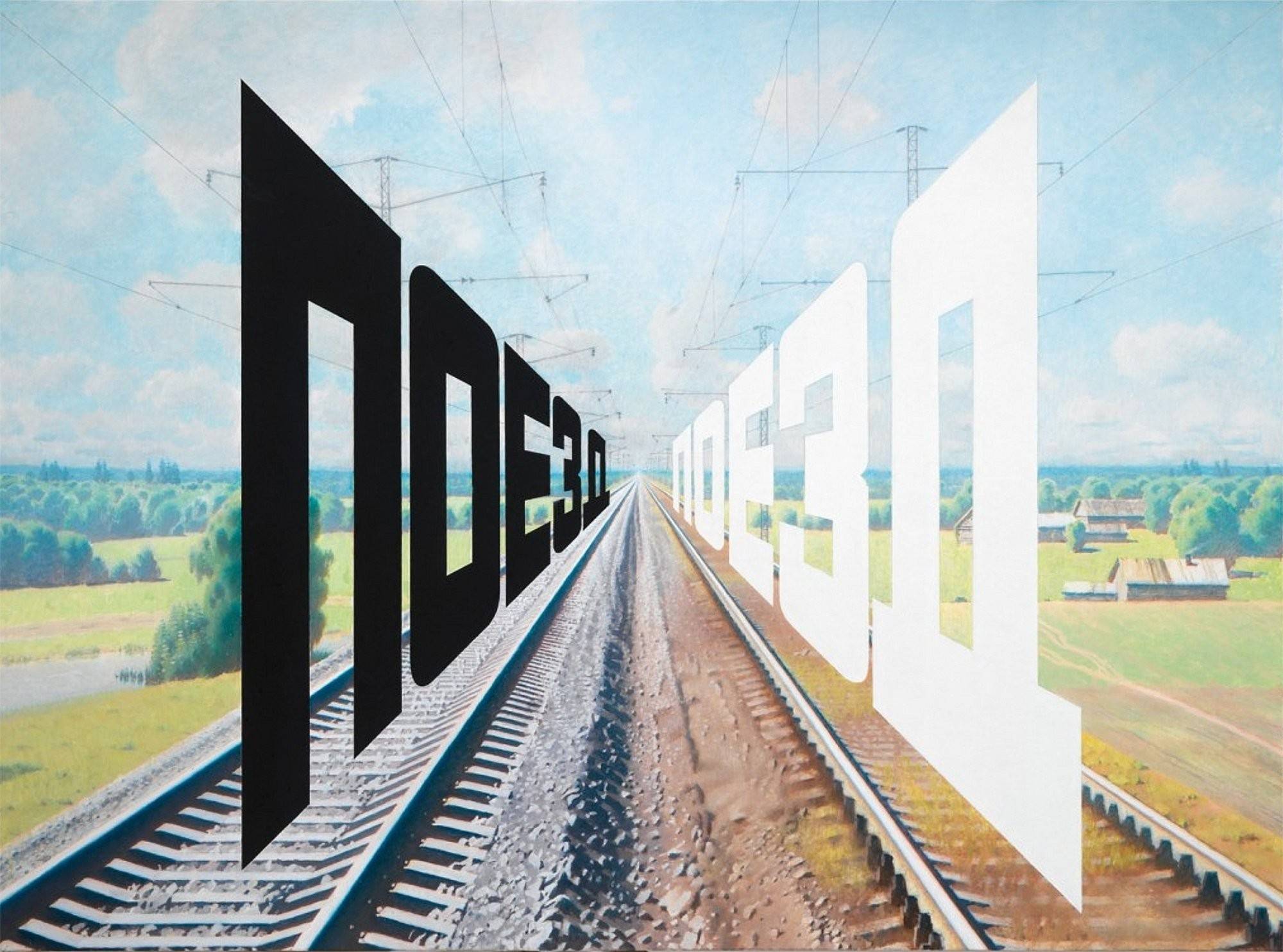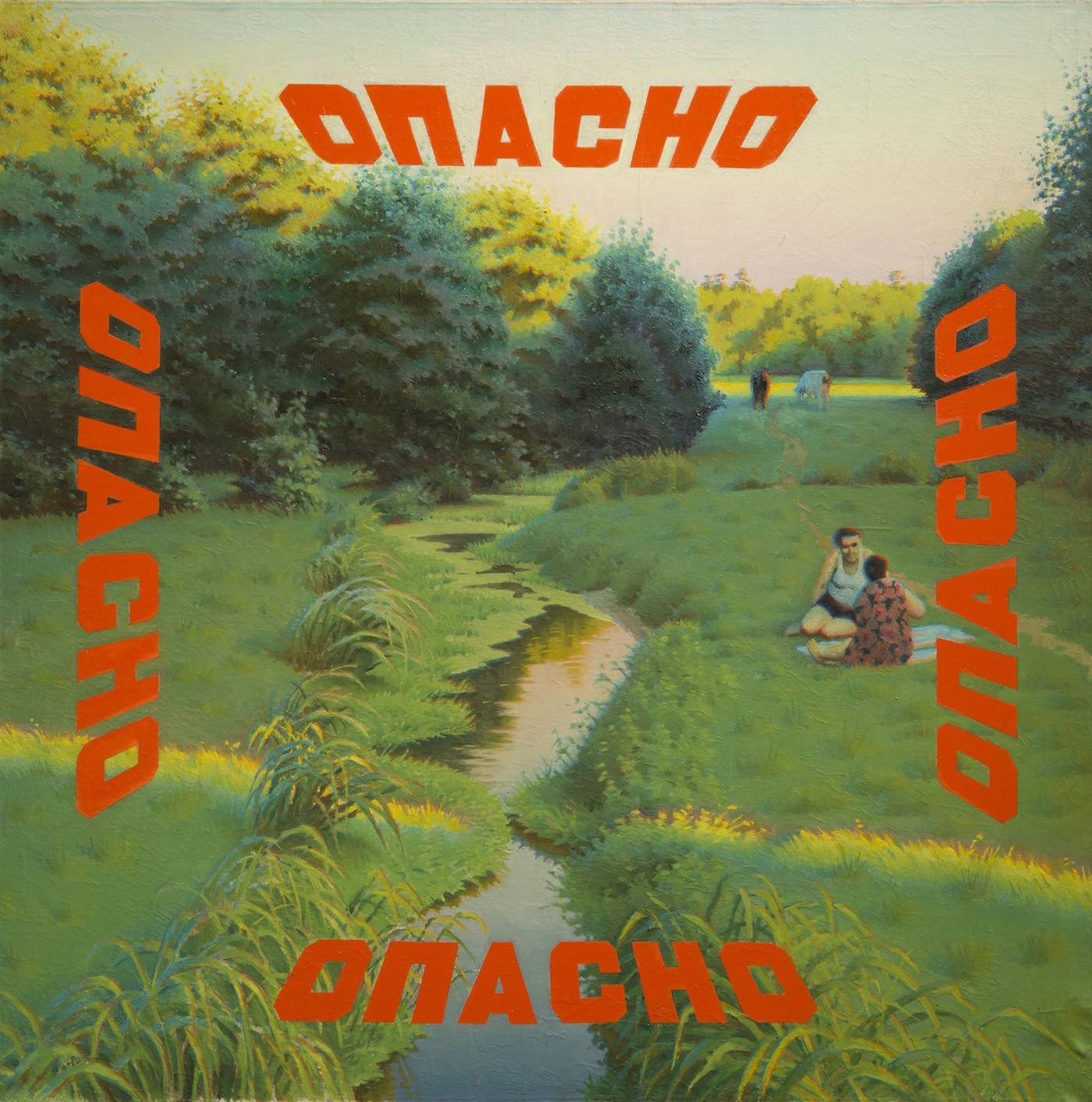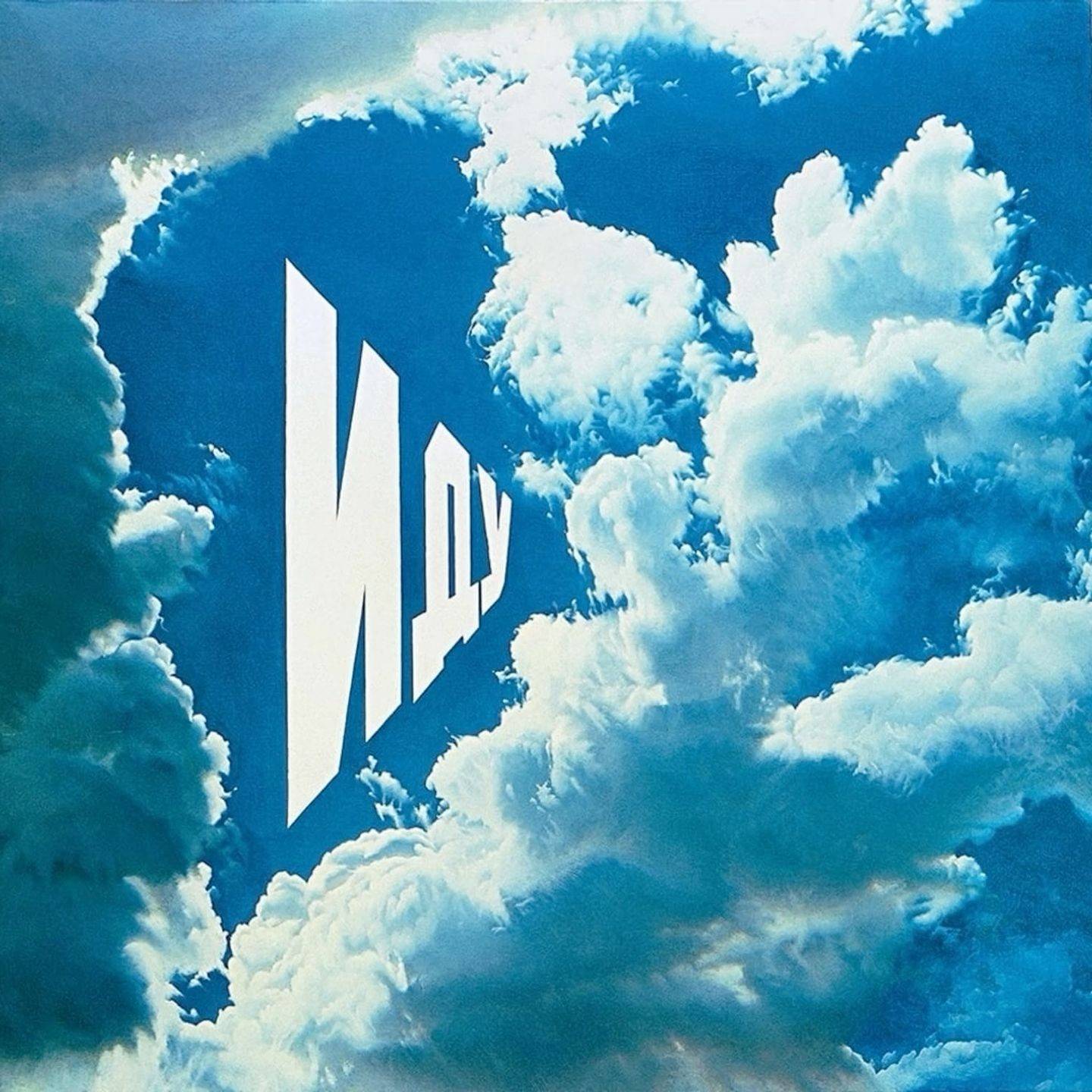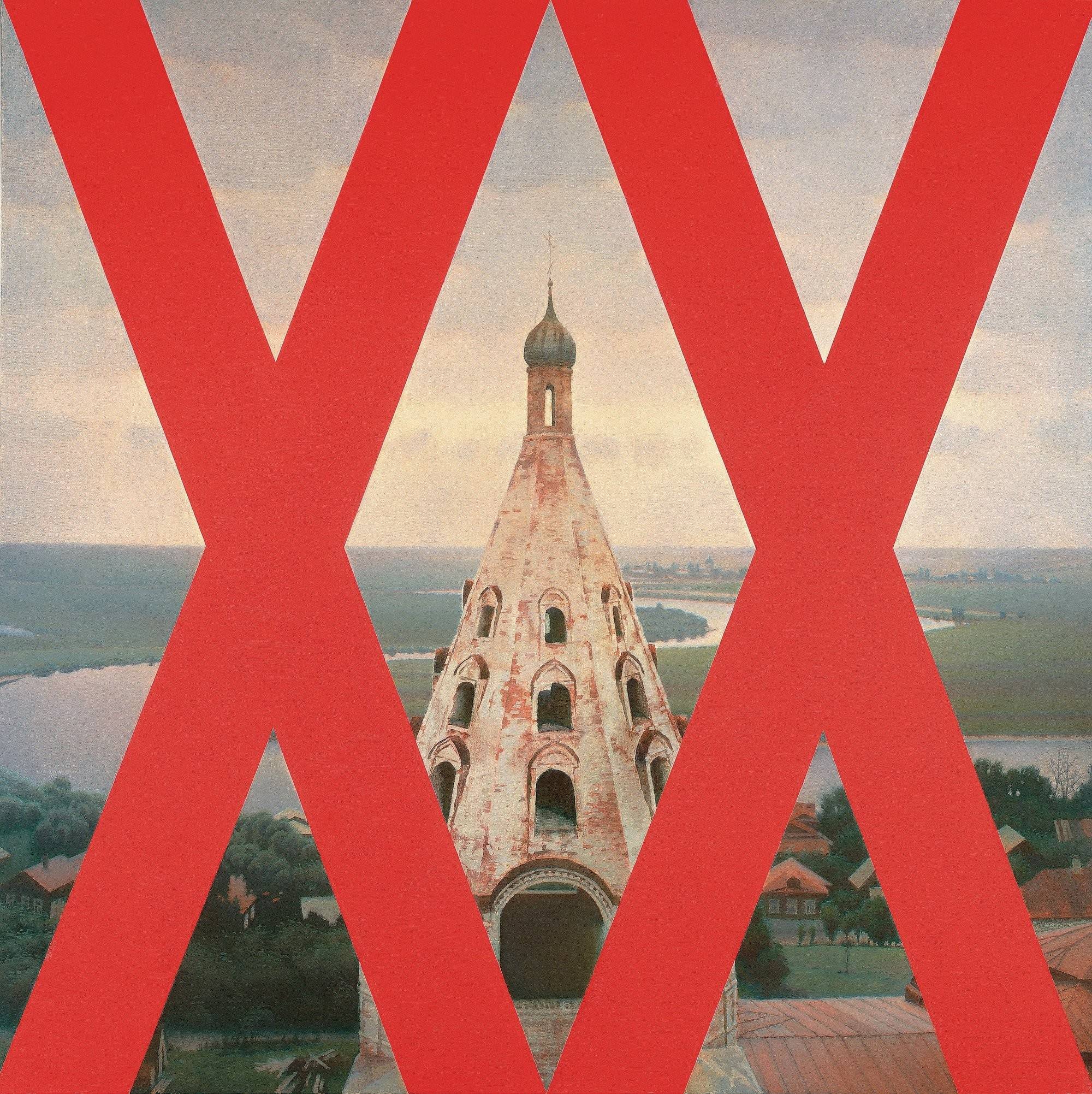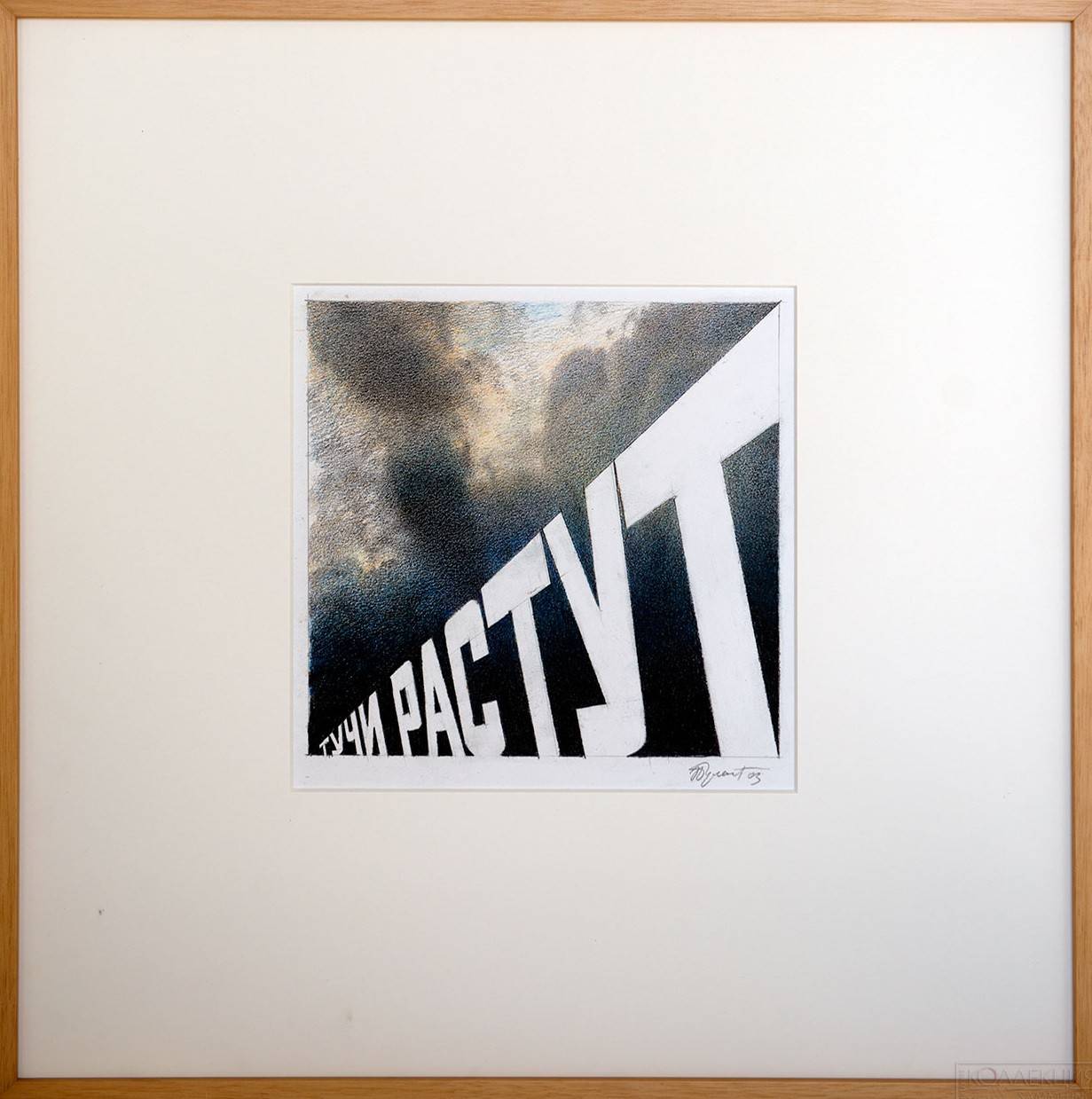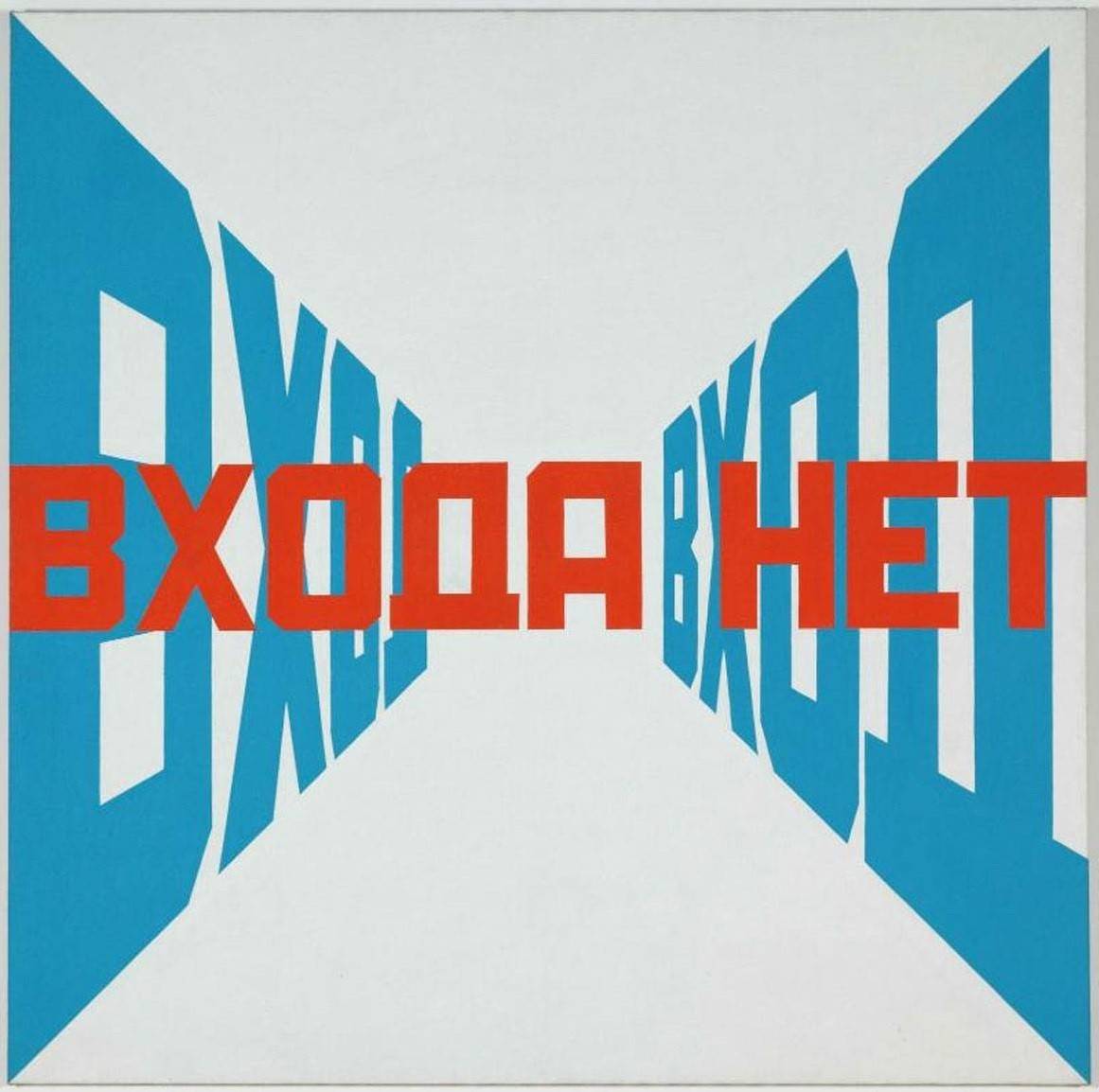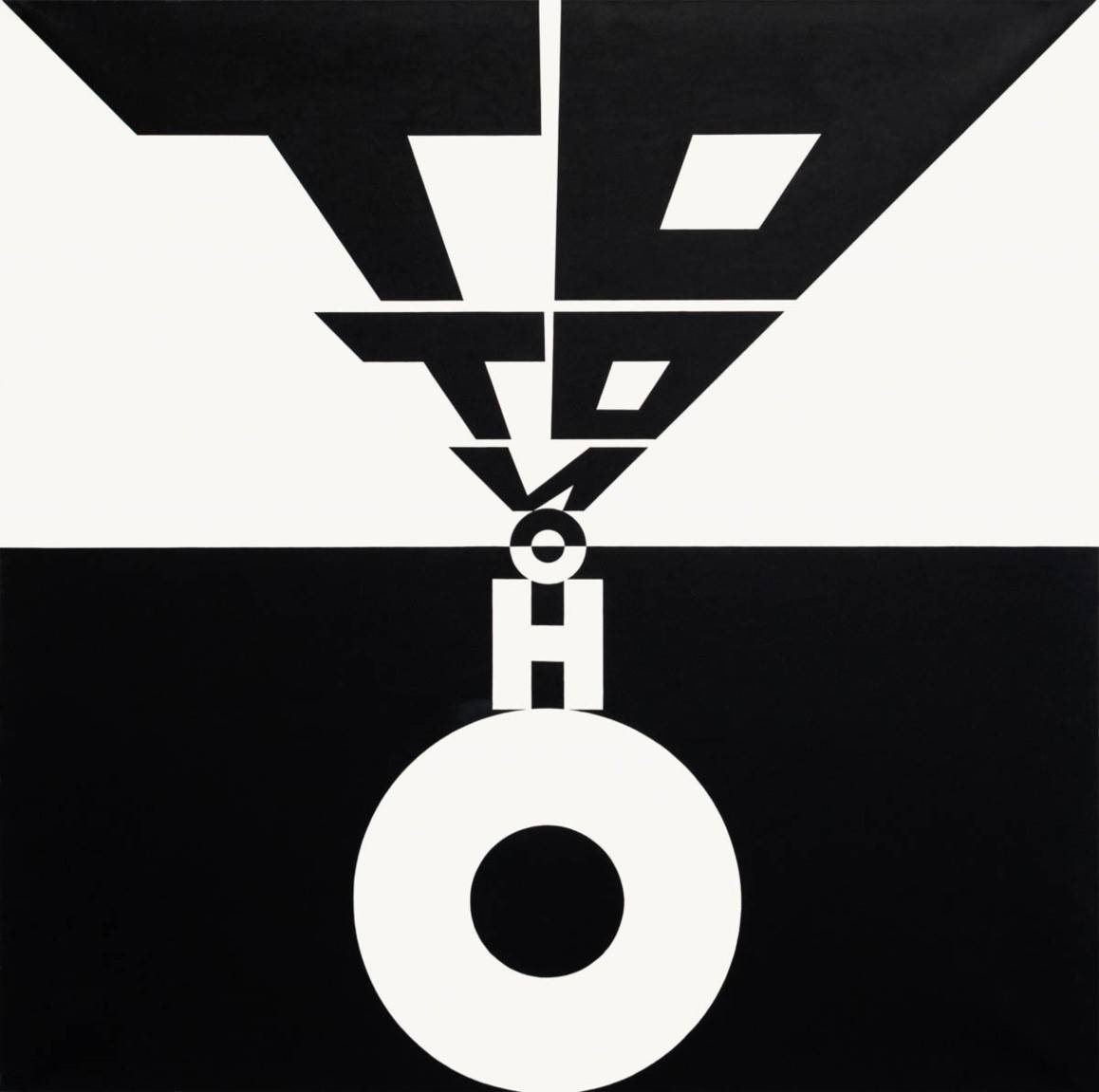
Шрифт и вызов
в РОСИЗО проходит выставка «Эрик Булатов. Избранные страницы»
Эрик Булатов может нравиться и не нравиться, вызывать восторг или раздражение, интерес или зевоту, но факт остаётся фактом — булатовский почерк узнаваем. Это как раз тот случай, когда забываешь имя-фамилию художника, но его картины вспоминаются слёту — достаточно разок приметить. Талант — быть единственным в своём роде, и не только потому, что сюжеты бьют по глазам яростью шрифтов — тут всегда двойной, тройной посыл. Картины Булатова и приятно удивляют, и слегка фраппируют. Иногда невозможно понять, иронизирует ли мастер или, напротив, пылает пафосом. Или то и другое одновременно?
Его величают и родоначальником соц-арта — направления, препарирующего советскую символику, — и московским концептуалистом, и гиперреалистом, да ещё — бунтарём-диссидентом и творцом своеобразной «летописи» СССР — той страны, которую он то ли обожал, то ли презирал, то ли испытывал к ней странное чувство, кое легче всего описать строками Лермонтова: «Люблю отчизну я, но странною любовью! / Не победит её рассудок мой». В любом случае, Булатов покинул Советский Союз не в 1970-х, как большинство диссидентствующих гениев, а в 1990 году, на пике перестроечных вакханалий.
В выставочных залах РОСИЗО сейчас проходит выставка «Эрик Булатов. Избранные страницы», где зрителю предлагается постичь творческую манеру автора, сочетающую в себе вербальные и визуальные основы. Картины Булатова изображают, а заодно говорят, кричат, шепчут, призывают. В них чувствуется дух постреволюционного авангарда с плакатными шрифтами и коллажной техникой.
Художник не сразу нашёл свой путь. Среди экспонатов — ранняя вещь Булатова под названием «Разрез». Это — опыт абстрактного видения и попытка преодоления плоскости холста. Свет, разложенный на цвета спектра, на фоне глубокой черноты космоса — это схоже с оптическими иллюзиями. Картина изысканна — в ней легко найти какую-нибудь мудрёную философию, но сие необязательно. Булатов писал красиво и никогда бы не стал уродовать натуру во имя «непохожести» на соцреалистов.
Булатов был требователен к себе и поэтому — сомневался. Он вспоминал примечательный разговор с Робертом Фальком: «Когда я принёс Фальку свои работы, он очень внимательно смотрел, а потом спросил: «А что вы сами думаете о своих работах?» Я признался в своём отчаянии и бессилии, потому что видел, что к искусству всё, что я делаю, не имеет отношения. И тогда он мне сказал: «Может быть, я вас утешу, а с другой стороны, наоборот, огорчу. Ваше признание свидетельствует о том, что вы сейчас в очень хорошей творческой форме. А эти сомнения будут сопровождать вас всю жизнь». Замечательные слова Фалька полностью сбылись». Потом начались эксперименты с буквицами и словами — они врывались в пространство фабул, подчёркивая задумку или же, напротив, отрицая её. Главный конфликт — между свободой и несвободой, меж «да» и «ни за что». Влекущая синяя надпись «Вход» перекрывается красной: «Входа нет». Как в том фильме – добро пожаловать или посторонним вход воспрещён. Так случается — и возможность предстаёт невозможностью. Всё — жизненно.
Часто булатовские ребусы — это жёсткий конфликт изображения со словом. На картине «Опасно» мы наблюдаем свежую зелень и отдыхающую парочку, однако по периметру идёт воспретительная надпись. «XX век» — римские цифры дважды зачёркивают пейзаж с шатровой церковкой. Это не столько богоборчество коммунистов, сколько полное переиначивание всего и вся — уход от патриархальности, форсированный урбанизм, учащение ритма.
Ещё одна важная тема — стремление вырваться из тенёт, причём имеется в виду вовсе не «тоталитарный» СССР — многие сюжеты написаны после переезда в Париж. Это — желание понять недостигаемое. «Свобода есть» — конфликт плакатной пустоты с волевым порывом. Слово рвёт казённый лозунг и летит в беспредельность. «Иду» — белые буквы, уносящиеся в небо. Стезя к Богу. «Поезд» — рельсы, бегущие на край земли, а дорога, как цель. Несмотря на то, что картина создана в середине 2000-х, она отражает настроение шестидесятников — к этому поколению принадлежал и Булатов.
В те годы молодёжь вслед за Юрием Визбором пела: «Дороги трудны, но хуже без дорог». Сесть на поезд и укатить куда-то в необозримые дали, с рюкзаком и гитарой; выйти на полустанке и вдохнуть запах незнакомых соцветий — это ли не счастье? Но та звеняще-трубящая дорога оказалась маршем в никуда. Шестидесятничество завяло, не успев как следует расцвести. В экспозиции нет картины «Горизонт», а ведь она отражает генеральную мысль — манящее раздолье может закончиться тупиком.
Эрик Булатов — певец московских дворов и скверов. Его Москва — расслабленно-тёплая, как на картине «Живу — вижу». Горячие солнечные крыши, длинные тени, зелёный шум и утверждение — мол, если я живу, то я — вижу, а видение – синоним жизни. Для художника это аксиома. Иной вариант на полотне «Вид Москвы из Мадрида» — тёмные силуэты на алом фоне. Кому-то город покажется Мордором, а кому-то — эффектным сновидением, царством теней и сполохов.
«То-то и оно» — диалог белого с чёрным. Василий Кандинский в колористической теории именует белый цвет «ничто, которое юно, или ещё точнее — это ничто доначальное, до рождения сущее», тогда как чёрный — «ничто после угасания солнца, как вечное безмолвие без будущности и надежды». Из двух «ничто» складывается мироздание. Это наша реальность, где всё состоит из тьмы и света, из противоборств и антитез. Чёрное — необязательно зло. Это просто ночь. Белое — это и выстиранное бельё, и первый снег, и — крылья ангелов. Макро- и микрокосм полярны.
Булатов любит противоположности — и цветовые, и смысловые. «Вверх — вниз» — серия из четырёх картин, где раскрываются все оттенки синего. Мотив головокружительной высоты — один из важнейших у мастера. «Найдём – разгуляться, где бы! Даёшь небо!» — как писал Владимир Маяковский. «Вверх — вниз» — это метафора бытия — мы то взмываем, то падаем, то — идём к Абсолюту, а бывает, что и деградируем. Задача — стремиться к высшему Я несмотря на то, что грешный ум тянет в пропасть. Булатов умел тонко явить лёгкость и тяжесть — при помощи всё тех же шрифтов и цветовых нюансов. «Тучи растут» — ощущение гнёта. Наплывает непогода, а тёмно-серые тона затмевают солнце.
На картине «Странник» изображён этакий шукшинский мужик, шагающий по весенней распутице. Воздух напоён предвкушением и свежестью, а природа словно бы подёрнута вуалью. Над головой странника неподвижно висят гербы СССР — наверное, кто-то скажет, что они — символ тирании, а по мне, это смотрится как строка из песни: «Человек проходит, как хозяин необъятной родины своей». Чем хорош Булатов? Он не раздавал клейма, но предлагал найти своё объяснение. На самом же деле «Странник» — это портрет Олега Васильева, коллеги и соратника, с которым Булатов частенько работал в паре.
А вот и «American dream», что повествует о тупиковых мечтах обывателя. Постер с белокурой фитнес-девушкой, накинувшей на плечо звёздно-полосатый флаг, — это иллюзия благополучия. На переднем плане — неопрятное существо, ночующее на улице. Вокруг — мусор и бумажные листы. Стена оклеена рекламой, но при этом — обшарпана и безобразна. Булатов не идеализировал Запад — он воспринимал его как вселенную контрастов.
Булатов не был чужд и постмодернистских вывертов и аллюзий. Типично обращение к приёму «картина в картине». Художник оригинально трактует «Явление Христа народу» Александра Иванова. Сонмище зрителей в зале. Их — толпа, и отнюдь не все поглощены искусством. Две экскурсоводши повествуют заученное. На лицах — усталость от беспрестанного пересказа дат, имён и атрибуций, которые (будем честны) мало занимательны. Разговор о божественном присутствии подменён энциклопедическими данными.
«Картина и зрители», где масса грубо заслоняет леонардову «Джоконду», — из той же серии. Наиболее известное произведение живописи, Мона Лиза сделалась элементом поп-культуры — она знаема и расхожа, как фантик, лейбл, вывеска. Все стремятся её узреть в реале, дабы заявить в соцсетях: «Я постоял рядом», да ещё добавить: «Ничего особенного». Профаны твердят о загадочной улыбке, а искусствоведы витийствуют о сфумато — нежнейшем размытии контуров, но Джоконда по-прежнему ускользает от пытливого разума.
Увлекательное занятие — рассматривать сюжет «Il tempo di Roma» — время Рима. Что есть римское время? Оно же — вечность. Перекличка эпох и течений, а блистательный Ренессанс вторгается в современность. Вот — люди, идущие по своим делам, но где-то там, за колоннами, возникают образы Боттичелли и Рафаэля, а мудрецы из «Афинской школы» шествуют навстречу итальянцам, редко задумывающимся, что являются хранителями сокровищ.
Потрясающе, но с творчеством Эрика Булатова и его друга Олега Васильева были преотлично знакомы советские дети — особенно девочки, обожавшие «принцесс». Дуэт Васильев — Булатов рисовал дивные иллюстрации к сказкам Шарля Перро, Сельмы Лагерлёф и Ганса Христиана Андерсена. Картинки преисполнены изящной прелести, элегантности, грации. Второй раздел экспозиции обращён к этим чародейным дарам — перед нами полка с книгами и «уголок иллюстратора», увенчанный настольной лампой. Концептуалисты, чтобы не выпадать из процесса, уходили в книжное иллюстрирование — это Виктор Пивоваров, Илья Кабаков и наши Булатов с Васильевым. Сотрудничество с издательствами давало заработок и причастность к обществу. Отклик — восторг детворы!
Тоненькая Золушка в златом наряде едва касалась пола хрустальной туфелькой, а её сестрицы поражали пышностью куафюр, взятых прямиком из Версаля капризницы Антуанетты. Эфирность Спящей Красавицы напоминала о юных герцогинях Боттичелли и прочих девах эры кватроченто. Феи в роскошных уборах — эннен и эскофьон-ан-корн — буквально парили в воздухе. Забавный король в напудренном парике и принцесса, одетая в платье с турнюром, встречали Кота в сапогах. И летел гусь Мартин с Нильсом «на борту» в полуфантастическую Лапландию. И страдала Элиза в ожидании братьев, превращённых мачехой в лебедей. Каждую страничку оплетали филигранные виньетки — то с рокайлями, то с розами. Булатов и Васильев прослыли добрыми сказочниками, потому что были прекрасны душой, а их нонконформизм проистекал не из фанфаронства иль безумия.
Эрик Булатов скончался в прошлом году, оставив после себя изумительное наследие, и в экспозиции показана лишь малая его часть. «Живу — вижу» — таков был его девиз, сопровождавший поиски всесветной гармонии.